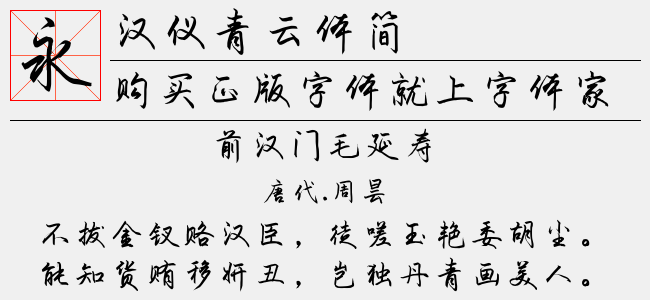
汉仪青云体简
字体作者:汉仪字库
字体名称:汉仪青云体简
字体字数:6763个汉字及26个英文大小写字母
字体家族:汉仪字库
书体类型:书法字库类
字体公司:北京汉仪科印信息技术有限公司
汉仪青云体简
汉仪青云体简是出自汉仪字库的一款非常不错的中文字体。非常的古朴端庄,仪态优美,很适合用于文字排版、出版印刷、海报设计等相关领域。